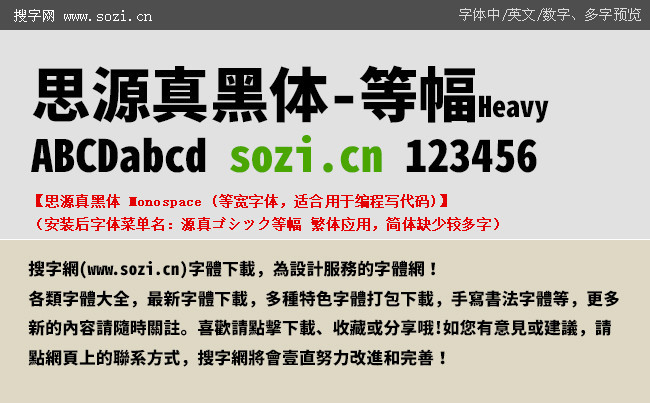
思源真黑體-等幅Heavy
搜字網(wǎng)給大家提供一款思源真黑體-等幅Heavy中文字體下載,思源真黑體字體是源于Google的開(kāi)源字體思源黑體,保留了思源黑體原版的優(yōu)雅以及高可讀性的特色,并在思源黑體的基礎(chǔ)上做出了變化,使得整套字體看起來(lái)更加銳利清晰。等寬字體 GenJyuuGothic - Monospace適合用于編程寫(xiě)代碼。